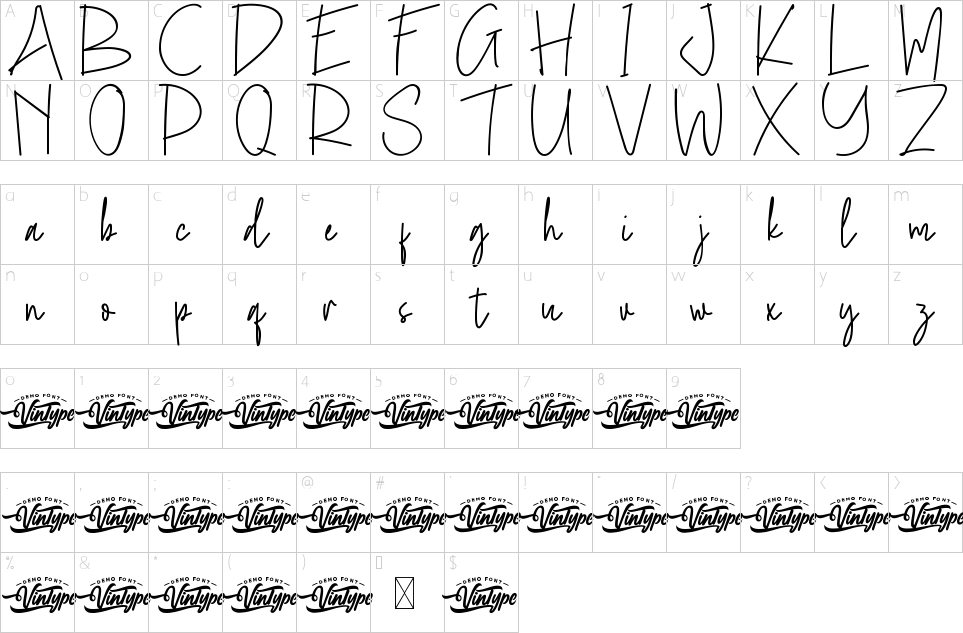
A fonte Monica Eleora oferece um charme elegante e sofisticado, perfeita para projetos que exigem um tom mais formal e harmonioso. Desenhada pelo VinType, esta fonte é uma excelente escolha para aqueles que buscam uma solução gráfica cuidadosa e delicada. Monica Eleora foi projetada para dar vida a textos, proporcionando um toque de elegância em qualquer layout, seja para materiais de escrita corporativa, designs de logotipo ou até mesmo para a criação de materiais educacionais. Com seu design cuidadosamente elaborado, Monica Eleora é uma fonte de graça perfeita para quem procura uma alternativa elegante e diferenciada. Com o download fácil e gratuito da Monica Eleora font, é simples criar um design único e sofisticado. Completando a sua coleção de fontes, Monica Eleora é uma escolha inteligente para designers e amantes da arte visual.